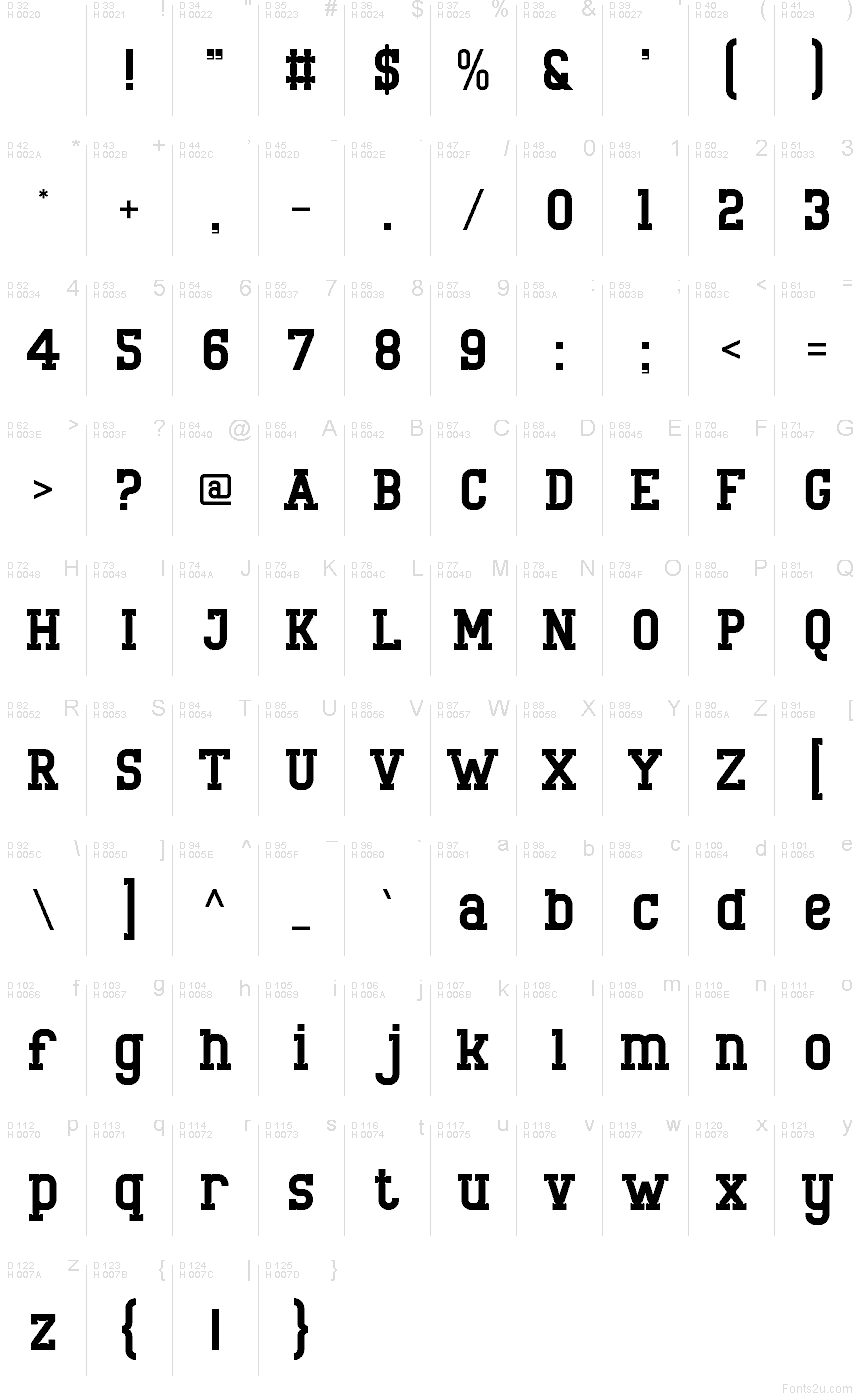
Merhin Regular
ErmediaStudioによるMerhinは、力強い新聞の題字を思わせる無料のセリフ体です。重みのあるスクエアな字形とどっしりしたセリフが、インクをしっかり乗せたような濃密な存在感を生み出し、文字間の詰まったリズムが単語全体を引き締めて見せます。印象はあくまで力強くストレート。それでいて、ブロック感のあるカーブにはほんのりレトロな温かみがあり、硬派な雰囲気をほどよくやわらげています。
Merhinを使えば、見出しは瞬時に重厚感と信頼感を獲得できます。この無料フォントは、ポスター、雑誌の表紙、書籍タイトル、ロゴ、バッジ、Webサイトのヒーローテキストにぴったりです。短い言葉でもしっかりインパクトを出したい、しかも冷たく無機質には見せたくない——そんな場面で特に映えます。すっきりした情報設計にするなら、タイトルにはMerhin、本文には軽めのジオメトリックなサンセリフを合わせるのがおすすめ。サイズも通常より1〜2段階大きめにすると、この書体の骨太な個性がより際立ちます。